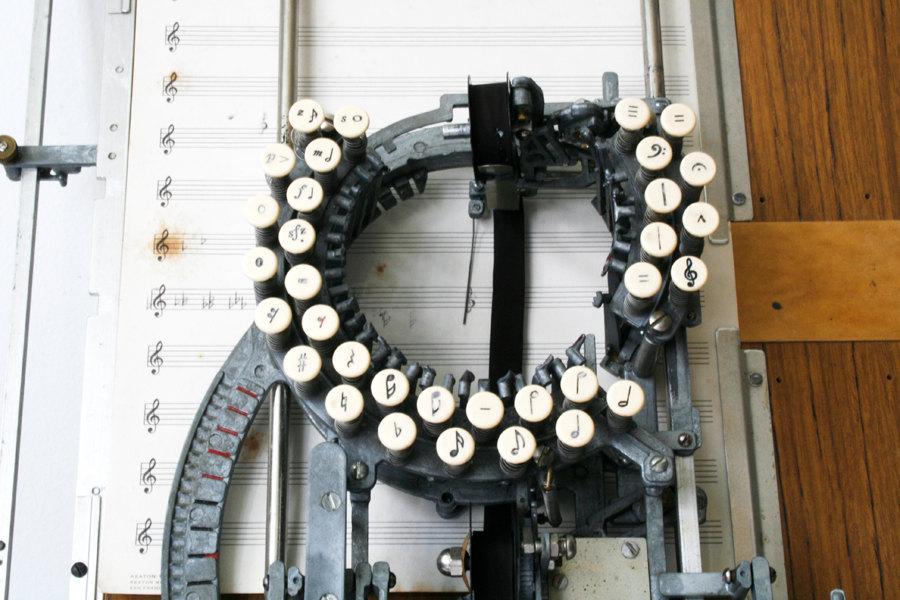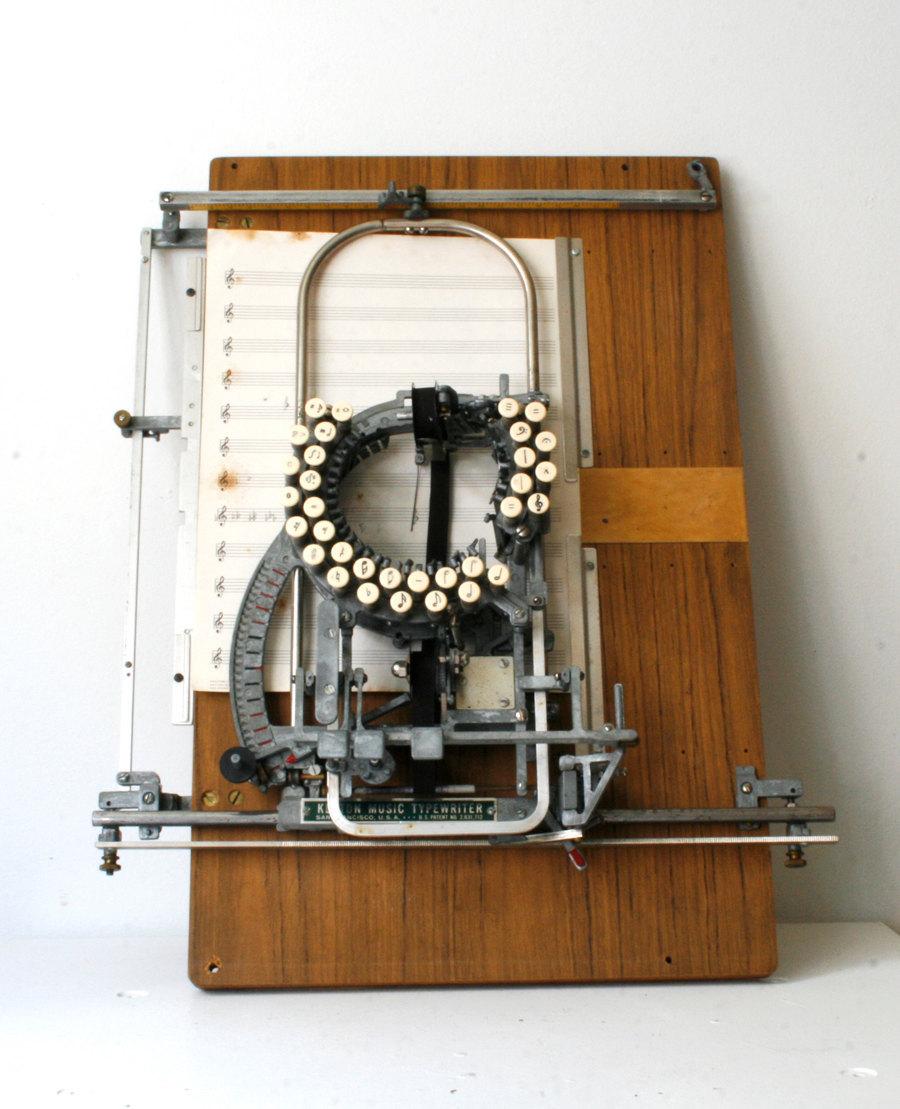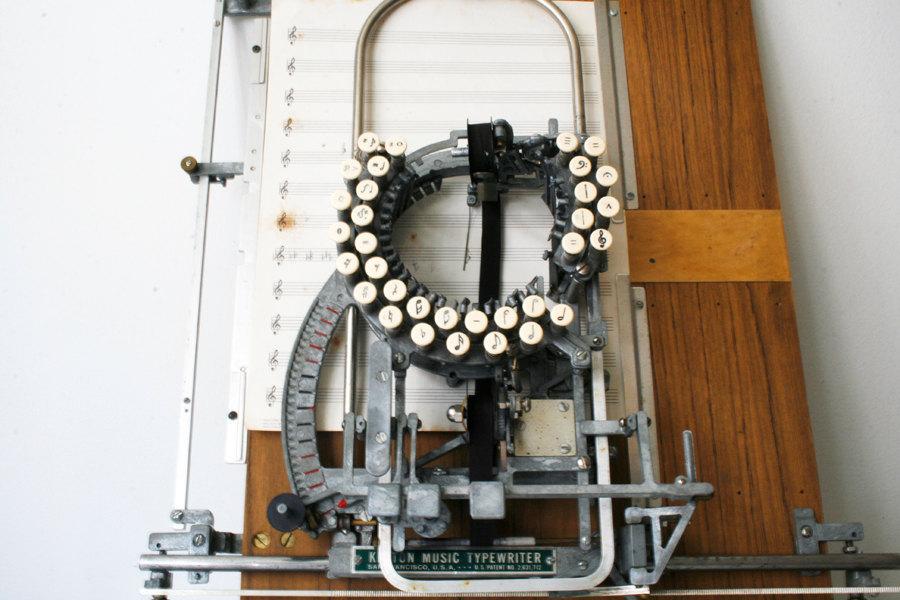
Na ja, für die Angehörigen des Medizinisch-Industriellen Komplexes sind solche Krankheiten möglicherweise wirklich ein Grund zur … sagen wir mal … professionellen Zuversicht und eine Quelle nimmer versiegenden Wohlstandes. Ob die Zielgruppe (»Ihr Exemplar zum Mitnehmen«) das auch so gelassen sieht, mag dahinstehen.
Wobei ich, abgesehen zwischen der grauenhaften Diskrepanz zwischen Titel und Bild, das Logo ja wirklich spannend finde. Da haben sich Leute Gedanken gemacht, die einiges von der Materie verstehen. Es ist Klisché-genug um Otto Normalverbraucher den gewünschten Eindruck zu geben, aber für mich als Spezialisten lädt es durchaus auch zum Nachdenken ein.
Zwar kein typografisches, aber dennoch ein Fundstück. Damit ihr endlich wisst, was richtige Männer ausmacht.
Hauptsache, der Mittelständler kann sich selber auf die Schulter klopfen.
Freiheit, die ich meine...
Gerade im Vorspann zu Meine Zeit wird kommen entdeckt, der vorhin auf 3sat nach Mahlers Achter lief.
das kam grad über designer-daily rein: Eine Schreibmaschine für Notensatz. Die würde ich ja liebend gerne mal in Aktion sehen. Können wir sowas nicht über die Forenkasse abrechnen? ;-)
Nachtrag: Bei eBay gib’s noch mehr Bilder.
mehr Bilder gefunden …
Die ist ja schon ganz chick find ich. Allerdings kann ich mich mit den i-plus-irgendwas-Ligaturen eher nicht anfreunden. Die s- oder c-plus-irgendwas-Ligaturen sind ganz schön, die hab’ ich bei der Master-Arbeit von meinem Freund für ein lateinisches Gedicht auch benutzt (in Linux Libertine gesetzt)
Und die Engländer tauschen sie einfach aus, wenn die Windel voll ist.
to change a baby: die Windel eines Babys wechseln
to exchange (something): (etwas) aus-/umtauschen
Z.B.:
Good morning, I need to change my baby.
— Certainly, feel free to use the bathroom over there, it has a changing table.
Good morning, I need to exchange my baby.
— Slowly step away from the child, you horrible, horrible person!
Wobei ich … das Logo ja wirklich spannend finde. Da haben sich Leute Gedanken gemacht, die einiges von der Materie verstehen.
Ist Krebs prinzipiell genetisch bedingt? Das wäre jetzt jedenfalls meine erste Assoziation.
Und hier ist das Begleitheft zu Ihrer Krebsdiagnose.
— Oh Gott! Meine DNA ist auch kaputt? Heißt das, dass ich keine Kinder haben kann?!
Im Prinzip: Ja.
Prima. Dann kann ich mich ja jetzt bedenkenlos rauchend in die pralle Sonne legen. :-P
Und damit erreichst Du auch nur hundertausende von Schäden pro Genom pro Zelle, welche wiederum zu fast 100% repariert werden. Die wenigen die nicht repariert werden resultieren in Mutationen, also genetischen Änderungen, welche eine Vorstufe zur Krebsentstehung sein können. Ich vermute Du hast es so interpretiert daß Krebs immer »vererbt« ist? Das ist natürlich Käse, Krebs ist in gewisser Beziehung die logische Konseqzuenz multizellulärer Organismen, genetische Prädispositionen erhöhen »nur« das Risiko. Genetisch bedingt ist Krebs trotzdem fast ausnahmslos (Ausnahmen bestätigen die Regel).
Kam gerade via tagesschau.de (Link um Artikel) rein:
:peng:http://www.spd-engenhahn.de/ :hammer:
Damit ihr wisst, was da auf euch zukommt und um es für die Nachwelt zu erhalten, falls die Autoren der Seite sich besinnen hab’ ich mal nen Bild angehängt …
Bild angefügt …
Passt! :)
Wow! Wow! Bow-wow! Der neue Kultlink linker Kultur. Danke für’s zeigen.
Und so ganz nebenbei, also einfach so … randbemerkt, leise rundum schmunzelnd … «Be-Be-Bbbergdorf» Engenhahn ist für mich ja der ganz grosse Kracher!
:mrgreen:
Herzlich,
Norbert II
Déformation professionnelle? Dachte doch tatsächlich an diesen Thread, als ich diesen Sommer durchs Puget Sound Navy Museum, Bremerton, WA, USA, schlenderte. Die Erklärung an der Wand bot diese Information:
Graphotype Machine, 1930s.
This 1930 graphotype machine stamped metal tags that identified pipes and cables used throughout a ship. Graphotype machines were also known as “dog tag machines”.
Grüsse,
Norbert II
Gibt es ein Gegenteil von Verpixelung?
http://koalastothemax.com/
Hach, das war jetzt eine wunderbar sinnentleerte Ablenkung für die Kaffepause in meinem gestreßten Alltag! Dank dafür! :gimmifive:
Das ist natürlich Käse, Krebs ist in gewisser Beziehung die logische Konseqzuenz multizellulärer Organismen, genetische Prädispositionen erhöhen »nur« das Risiko.
Eben, das meine ich ja. Ich hätte die Befürchtung, dass das Logo bei Nichtexperten den Eindruck hervorrufen könnte, dass Krebs nur was ist, das Leute mit »kaputtem« Erbgut betrifft. Oder ganz stark vereinfacht: Krebs ist angeboren und (nicht auch) ein Ergebnis von Lebensführung.
Na aber! Wie wärs mit einem Herbstspiel, (?) dessen Ziel es ist, das komplette Alphabet zu erstellen? Ein Serifen-R haben wir ja schon. (Zumindest für mich ist die Sache übrigens schwieriger, als sie auf den ersten Blick erscheint. Mein erster Versuch, einen Buchstaben halbwegs ansehnlich zu entpixeln, ist jedenfalls kläglich gescheitert.)